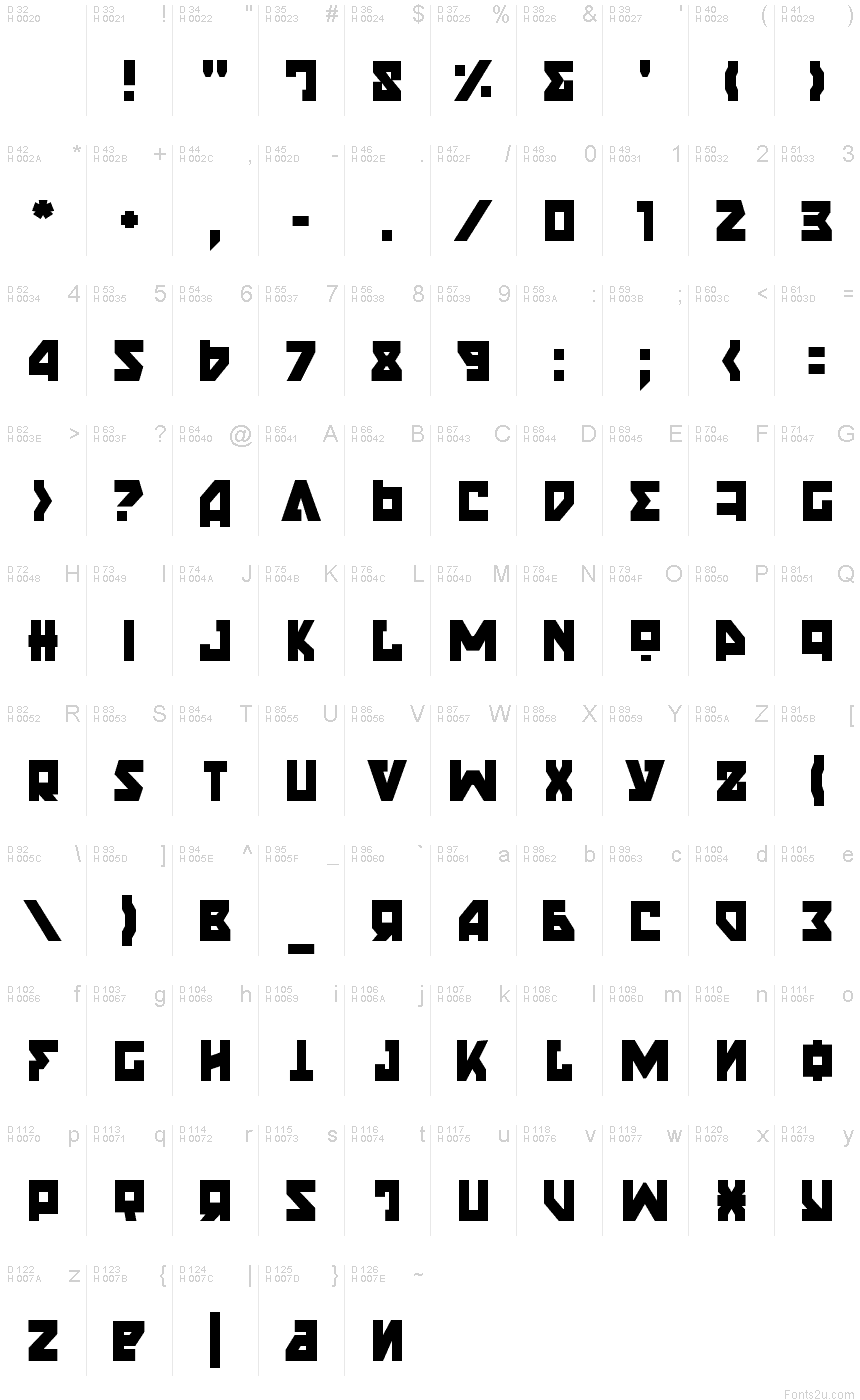
Nyet Semi-Condensed od Iconian Fonts to darmowy krój displayowy oparty na ostrych, kanciastych cięciach i blokowych, pionowych formach, które przywodzą na myśl liternictwo z plakatów radzieckich. Sylwetka kroju jest sztywna i architektoniczna, a ukośne nacięcia oraz klinowate łączenia nadają mu militantny, stemplowy rytm, unikając przy tym neutralnego, geometrycznego charakteru.
To świetny wybór do grafik inspirowanych propagandą, tytułów gier, plakatów eventowych, okładek płyt oraz opakowań, które wymagają surowego akcentu bloku wschodniego. Krój najlepiej sprawdza się w krótkich nagłówkach i logotypach, ponieważ zwarta bryła i ostre krawędzie nadają wyrazistym słowom odpowiednią siłę bez konieczności stosowania dodatkowych zdobień.
Nyet Semi-Condensed